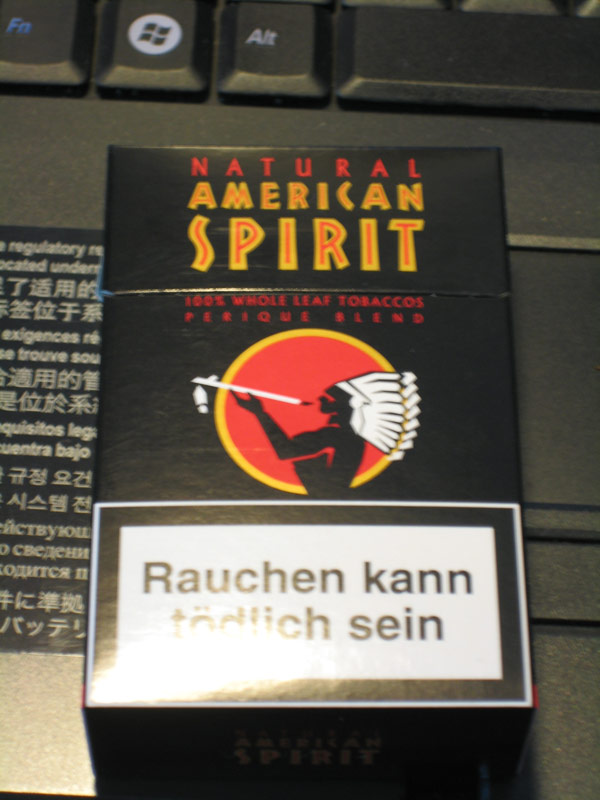
American Spirit Schriftart?
ich bin auf der Suche nach der Schriftart auf den Zigarettenschachteln von American Spirit, zu sehen hier:
Die innere Schrift würde im Prinzip schon reichen, die Kontur kann man ja relativ simpel noch selber drumbauen. Hat jemand vielleicht eine Idee?
Ich bin durch Google zwar auf eine Schrift mit dem Namen American Spirit gestossen, leider sind das allerdings nur Flaggensymbole und Ähnliches :?